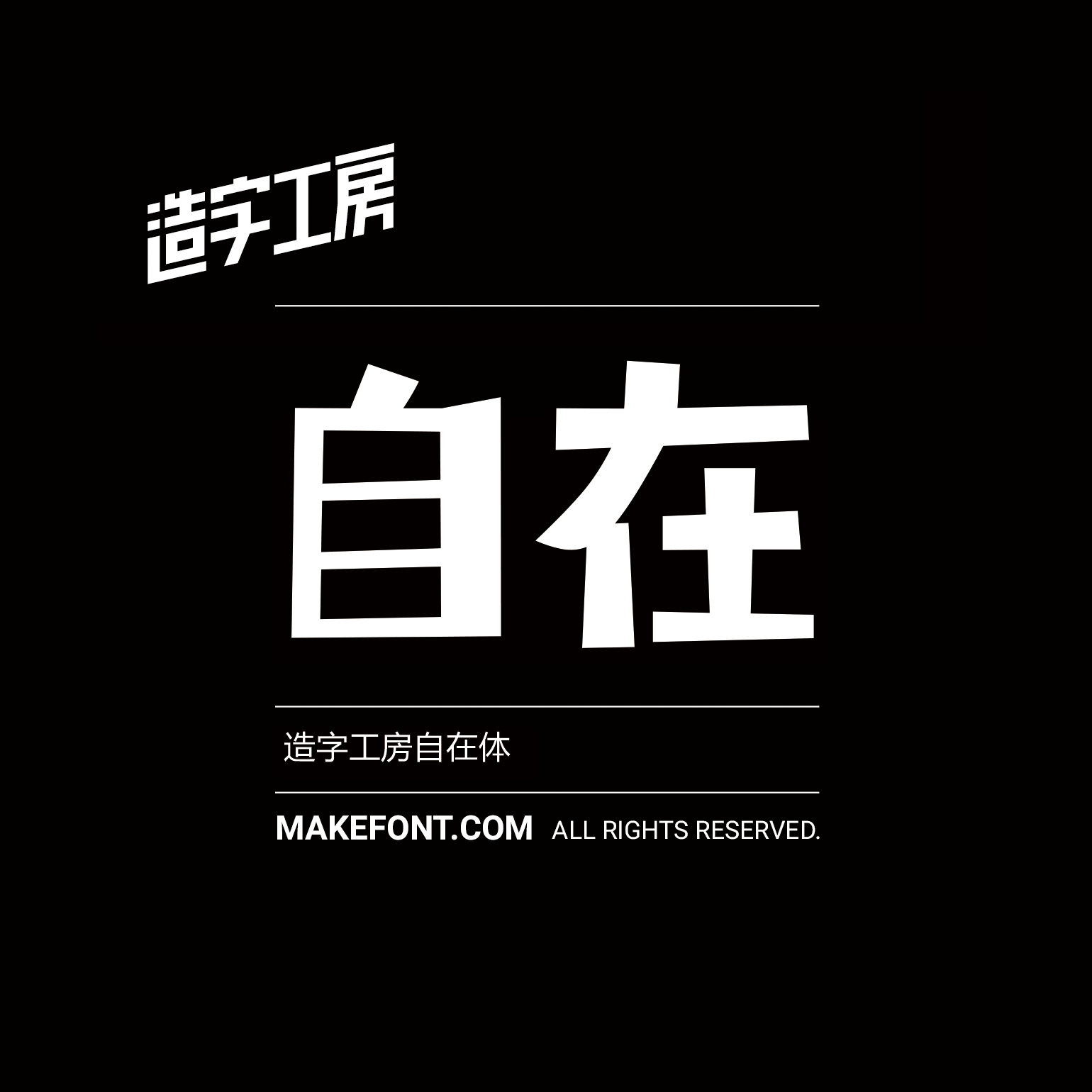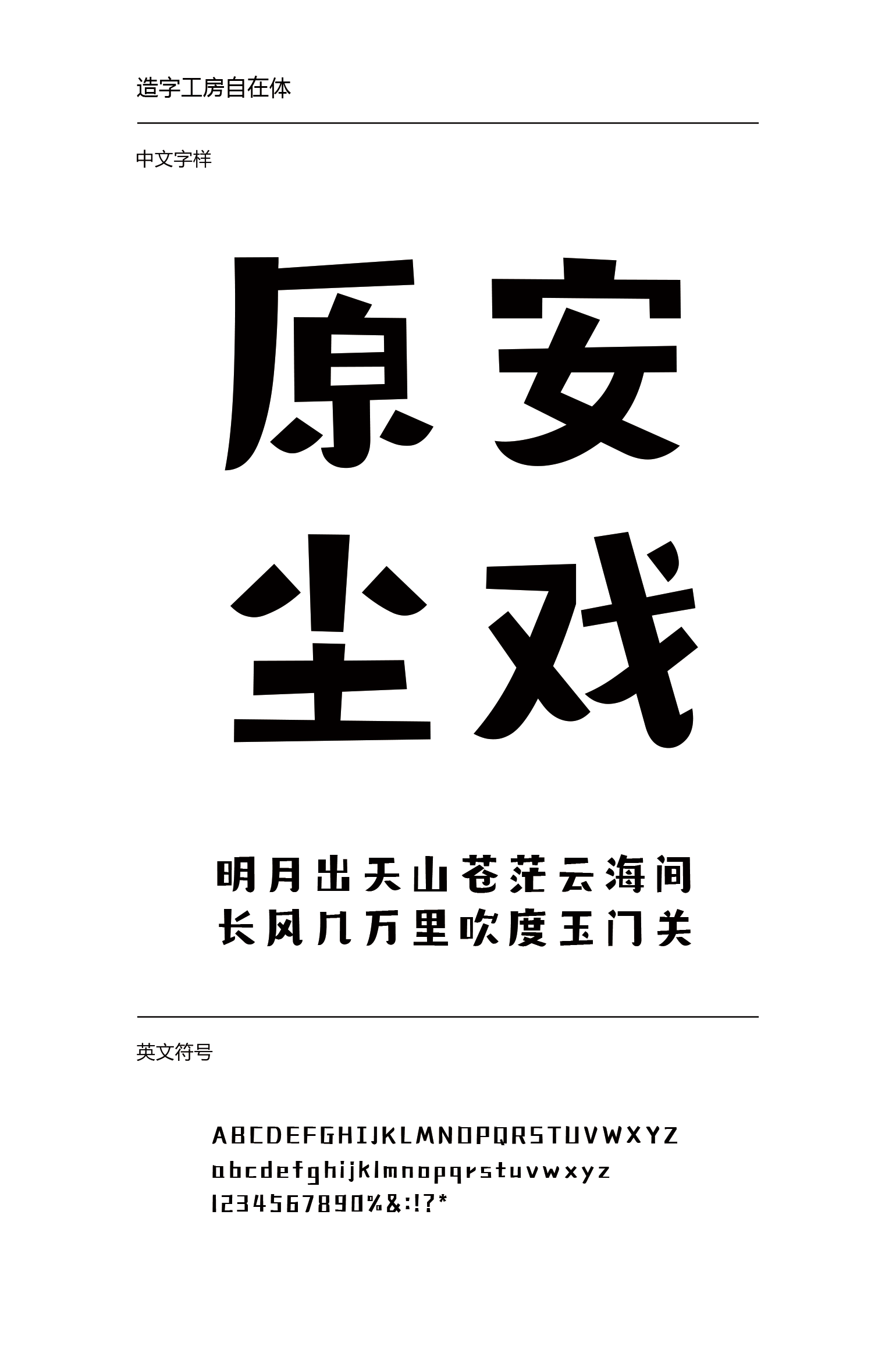
造字工房自在体设计说明
造字工房自在体MFZiZai_Noncommercial-Regular
造字工房自在体其笔画特点生动,活泼俏皮,体势灵动自由,疏密有致,别具丰润。兼具文艺雅致与质朴幼拙,天真烂漫卡通可爱。此款字体适用于儿童读物、报刊杂志标题、广告设计等视觉环境,有着极强的应用空间。本字体为简体字库,采用OpenType/CID格式,Adobe-GB1-5编码。基于中华人民共和国GB2312-80字符集标准,另按需添加101个汉字。共收容字数6864CJK汉字ASCII常用字符100个。